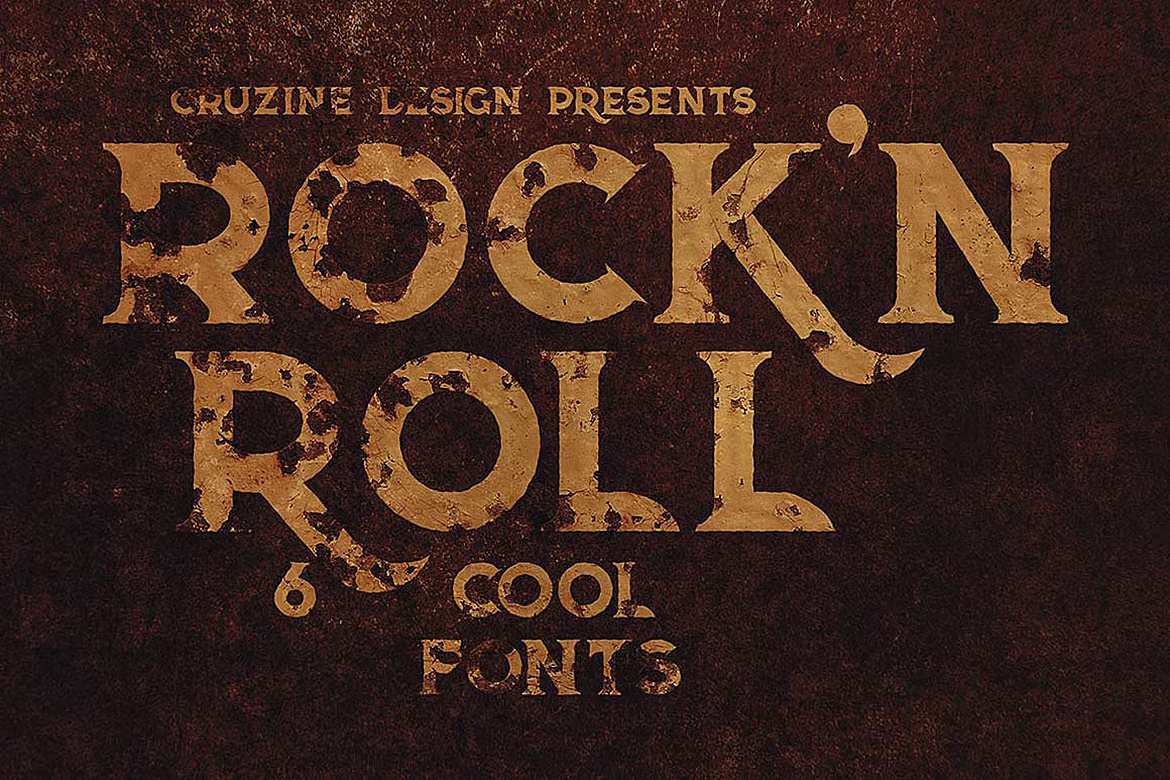
Rock’n Roll Font
Description de Rock’n Roll Font
Rock’n Roll Font est une police d’affichage de style créatif et audacieux pour vos nouveaux projets. Idéal pour les projets grunge/rétro/vintage !